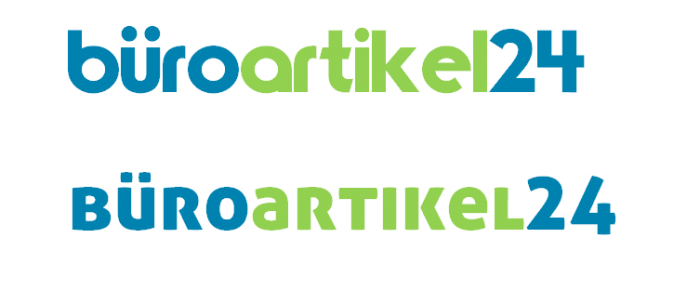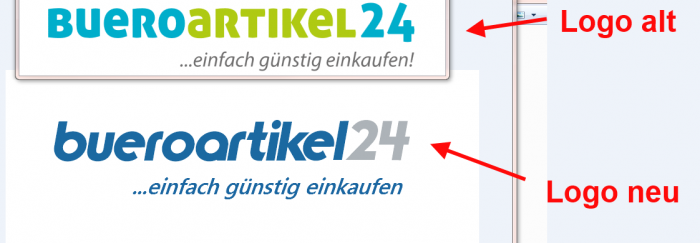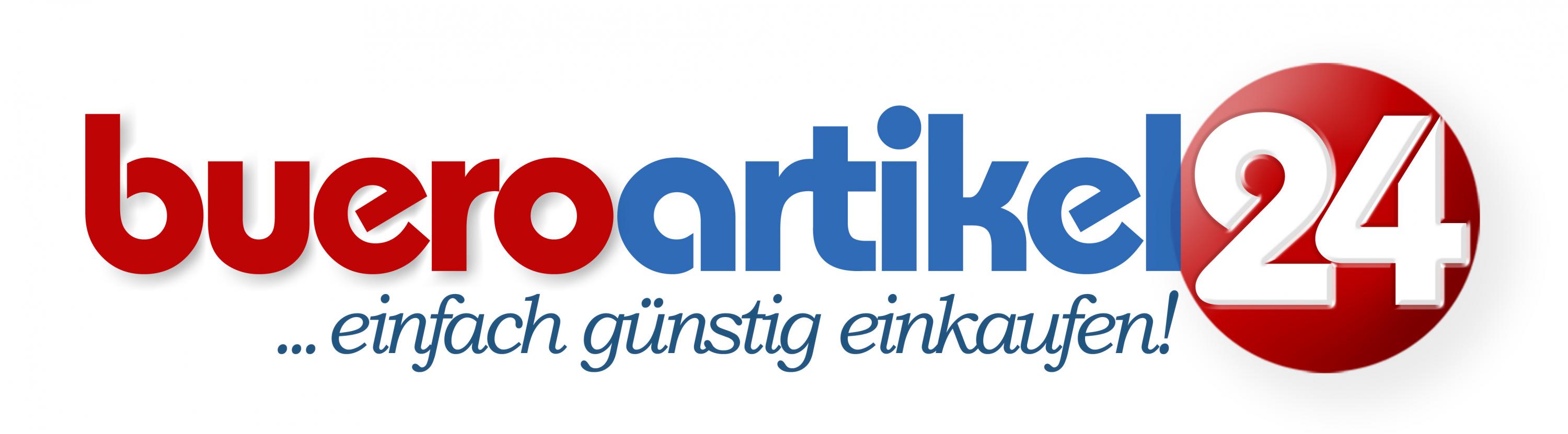
Suche passende Schriftart für Firmen-Logo
wir suchen für unseren Onlineshop ein neues Firmen Logo. Dazu habe ich mal ein Screenshot erstellt.
Was haltet Ihr vom dem Logo bzw. der verwendeten Schriftart?
Passt das die Farbe, das Logo zur Branche?
Vielleicht hat ja jemand zur Schriftart noch eine Idee, die man eher verwenden sollte.
Uns ist es wichtig, dass die Schrift gut lesbar ist und die "24" klar hervorgeht.
Die Experten kommen vielleicht noch, aber als ersten Laien-Eindruck:
- Der Name leidet ja technisch bedingt unter der Besonderheit, dass ein Leser büro zu lesen gewohnt ist, aber buero zu sehen bekommt. Um so mehr würde ich darauf achten wollen, dass sich am Übergang zum zweiten Wortbestandteil eine gute Lesbarkeit ergibt. Dazu muss die Schriftart so gewählt werden, dass sich o und a deutlich unterscheiden.
- Sofern die 24 so wichtig wie angegeben ist, sollte man sie durch die Farbwahl nicht abschwächen, sondern hervorheben.
Zu dem dunklen Blaugrau würde ich eher eine leuchtende Farbe als Kontrast wählen: Gelb, Orange, Rot, Grün und Magenta fallen mir dazu spontan ein.
Das alte Logo ist in Ordnung. Nichts besonderes, aber in Ordnung. Funktioniert auch auf der Seite im Gesamtzusammenhang.
Das neue Logo ist fürchterlich. Da passt gar nix und wie Carlito schon sagt, ist auch gar nicht ersichtlich, warum dies überhaupt entstehen soll. Entweder würde ich es beim alten belassen oder aber einen Grafikdesigner mit der Erstellung eines schlüssigen Corporate Designs beauftragen. Mit ein paar Schrifttipps alleine entsteht ja noch kein gutes Design.
Ja, das Logo leidet wirklich technisch bedingt unter dieser Besonderheit.
Bei Google ist es aber egal, ob man Büroartikel24 oder
bueroartikel24 sucht.
Sollte man lieber das Logo mit "ü" anstatt mit "ue" darstellen?
Die Gründe für das Redesign:
- Kunden können das Bueroartikel durch das "ue" im Logo schlecht lesen.
- die "24" kann nicht richtig erfasst werden.
Wie kann man das Logo besser aussehen lassen?
Die Gründe für das Redesign:
- Kunden können das Bueroartikel durch das "ue" im Logo schlecht lesen.
- die "24" kann nicht richtig erfasst werden.
In genau diesen Punkten ist das neue Logo ja ein Rückschritt bzw. keine Verbesserung.
Die »24« im alten Logo finde ich deutlich lesbar. »ue« könntest Du im aktuellen Logo mal probehalber durch den Umlaut ersetzen.
Kunden können das Bueroartikel durch das "ue" im Logo schlecht lesen
weshalb man das »ue« durch »ue« ersetzt? Tut mir leid, das verstehe ich nicht.
die "24" kann nicht richtig erfasst werden
Wieso? Das ist doch eine ganz normale 24.
Der einzige Fehler, den ich im Logo sehe, ist das fehlende Leerzeichen zwischen den Auslassungspunkten und »einfach günstig einkaufen« (denn das steht ja vermutlich nicht für »supereinfach günstig einkaufen« – dann wäre es richtig –, sondern für irgendein einzelnes Wort, und dann müsste ja auch ein Leerzeichen zwischen dieses ausgelassene Wort und »einfach«).
Hallo, habe nun nochmals das Logo kurz mit "ü" erstellt und die Farben ein wenig angepasst.
Die Abstände der einzelnen Buchstaben zueinander muss ich noch anpassen.
Was haltet Ihr davon?
Angesichts des Umstands, dass büroartikel24.de bereits – von einem Dritten¹ – registriert ist, würde ich mich weiterhin an der korrekten Schreibung des Domainnamens orientieren, der tatsächlich zu meinem Unternehmen gehört.²
Und ja, die Version in der Aller ist Welten besser.
1. der anscheinend versucht, mit einem Amazon-Provisionen Geld zu machen
2. und meinen Anwalt in die Spur schicken, um zu klären, ob wir wegen der extrem ähnlichen Konkurrenzdomain was machen können/sollten
Nein, das wollte ich keinesfalls anregen. Nur, dass angesichts diese (unvermeidbaren) Problems beim Rest ganz besonders auf Leserlichkeit geachtet werden sollte. Wie gesagt, einander sehr ähnliche o und a wären aus meiner Sicht zu vermeiden.
Ich finde den neuen Vorschlag auch deutlich schlechter. Bei dem Bild im ersten Beitrag habe ich mich gefragt, was an dem alten Logo falsch sein soll. Reißt sicher niemanden vom Hocker, aber funktioniert doch und wirkt freundlich. (Am ehesten könnte man noch die Unterzeile ersatzlos streichen, denke ich.)
Womit machen die Leute das eigentlich jetzt – seit es WordArt nicht mehr gibt? 3 Schatten, 4 Farben – aber immerhin nur 2 Schriften.
Edit: Mit Ensetzen stelle ich gerade fest, dass es das immer noch gibt, offiziell nennt MS das ein "Textverschönerungsfeature". :cry:
Die 4 Farben waren wohl Vorgabe … ;-)
ich finde, du solltest mit dieser Aufgabe einen Grafik-Designer beauftragen und dann muss diese Leistung auch entlohnt werden.